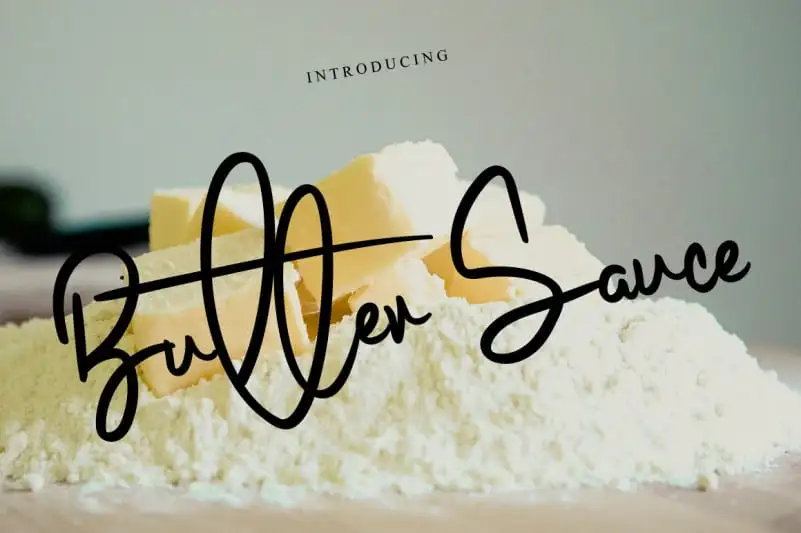
Butter Sauce Script Font – Download Grátis
A Butter Sauce Script Font é uma tipografia elegante e delicada, feita para aqueles que valorizam a transparência e os detalhes sutis na sua paleta visual. Esta tipografia cíntica e escrita à mão é perfeita para projetos que buscam um toque amigável e romântico. Suave e suave, ela se destaca em designs variados, dando um toque agradavelmente desenhoado e cheio de vida a qualquer projeto. Ideal tanto para cartões de aniversário quanto para embalagens de produtos pessoais, a Butter Sauce Script Font traz uma atmosfera leve e encantadora ao seu design. Enganche-se à sua paleta visual com um toque refinado que se adapta perfeitamente às suas necessidades.